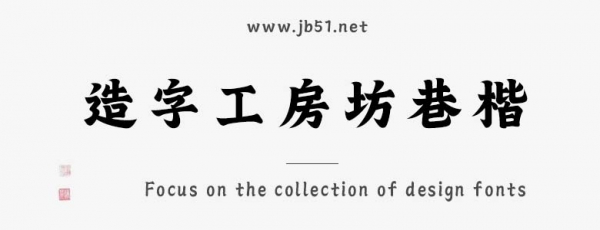
造字工房坊巷楷由上首造字字庫(kù)出品的字體,汲取楷書(shū)精髓,筆畫(huà)剛?cè)嵯酀?jì),起筆的輕盈、收筆的利落,盡顯灑脫。適合應(yīng)用于平面宣傳設(shè)計(jì)、網(wǎng)頁(yè)設(shè)計(jì),書(shū)法字帖等領(lǐng)域,需要的朋友可以前來(lái)本站下載。
造字工房坊巷楷,宛如市井生活的生動(dòng)縮影。它扎根民間書(shū)寫(xiě),汲取楷書(shū)精髓,筆畫(huà)剛?cè)嵯酀?jì),起筆的輕盈、收筆的利落,盡顯灑脫。結(jié)構(gòu)微有錯(cuò)落,恰似坊巷建筑的隨性之美,能精準(zhǔn)傳遞古韻,點(diǎn)燃觀者對(duì)煙火人間的溫情記憶。本字體為簡(jiǎn)體字庫(kù),采用OpenType/CID格式,Adobe-GB1-5編碼。基于中華人民共和國(guó)GB2312-80字符集標(biāo)準(zhǔn),另按需添加101個(gè)漢字。共收容字?jǐn)?shù)6864CJK漢字,ASCII常用字符100個(gè)。